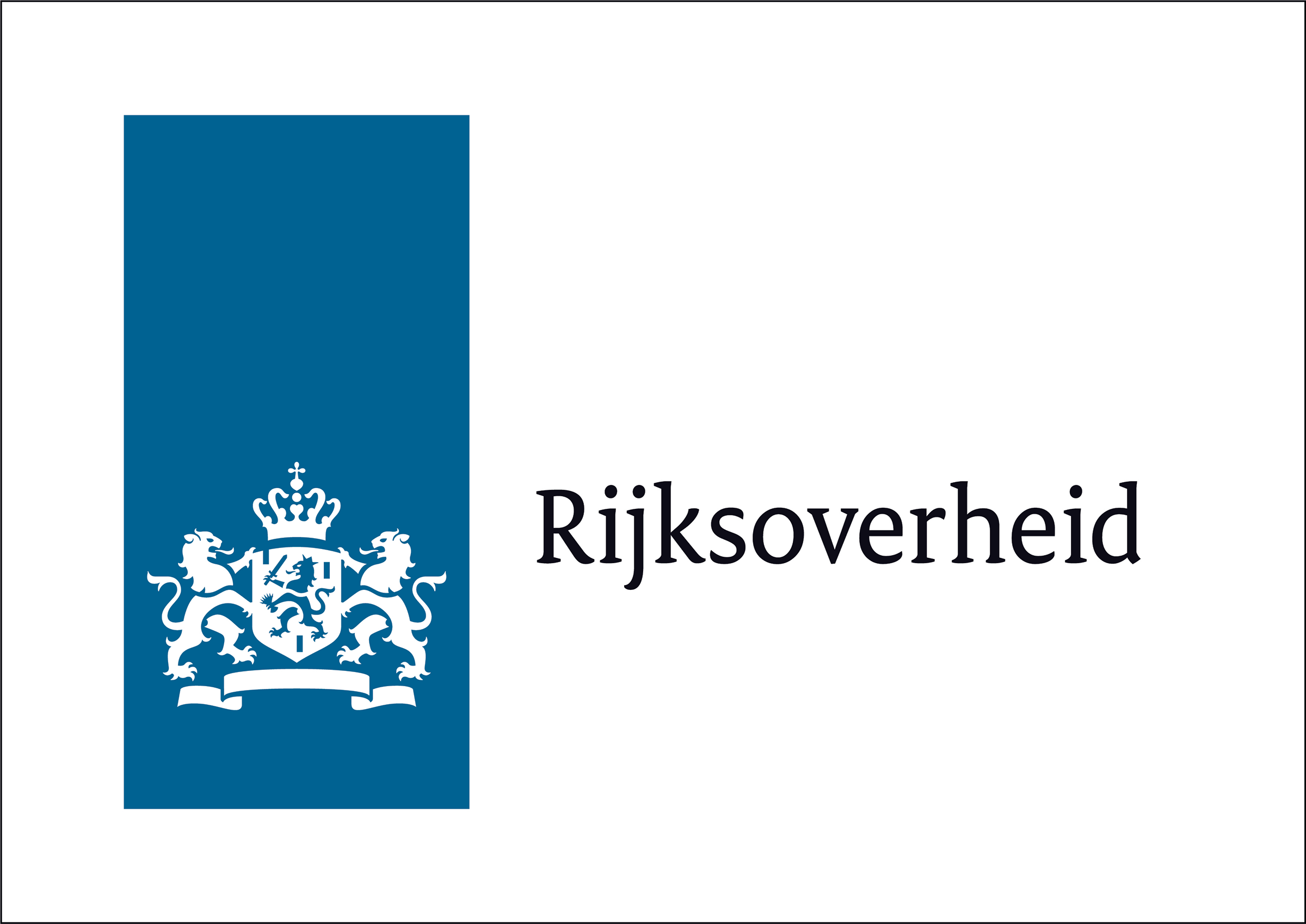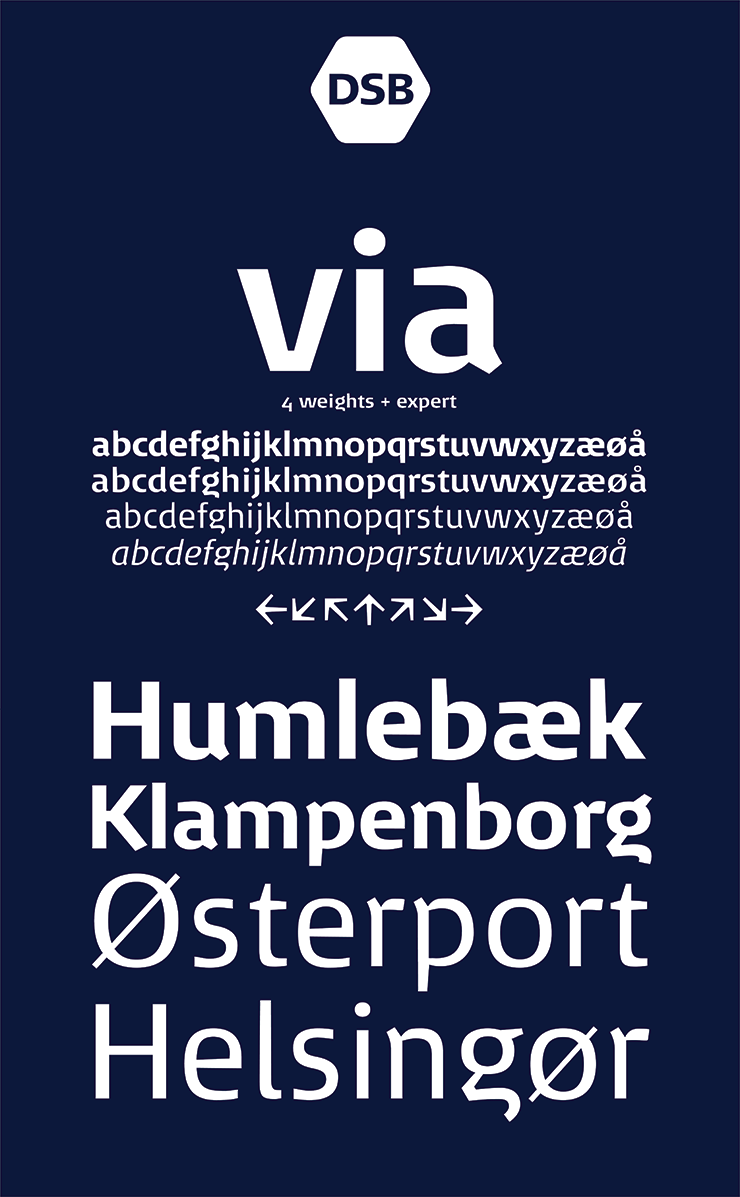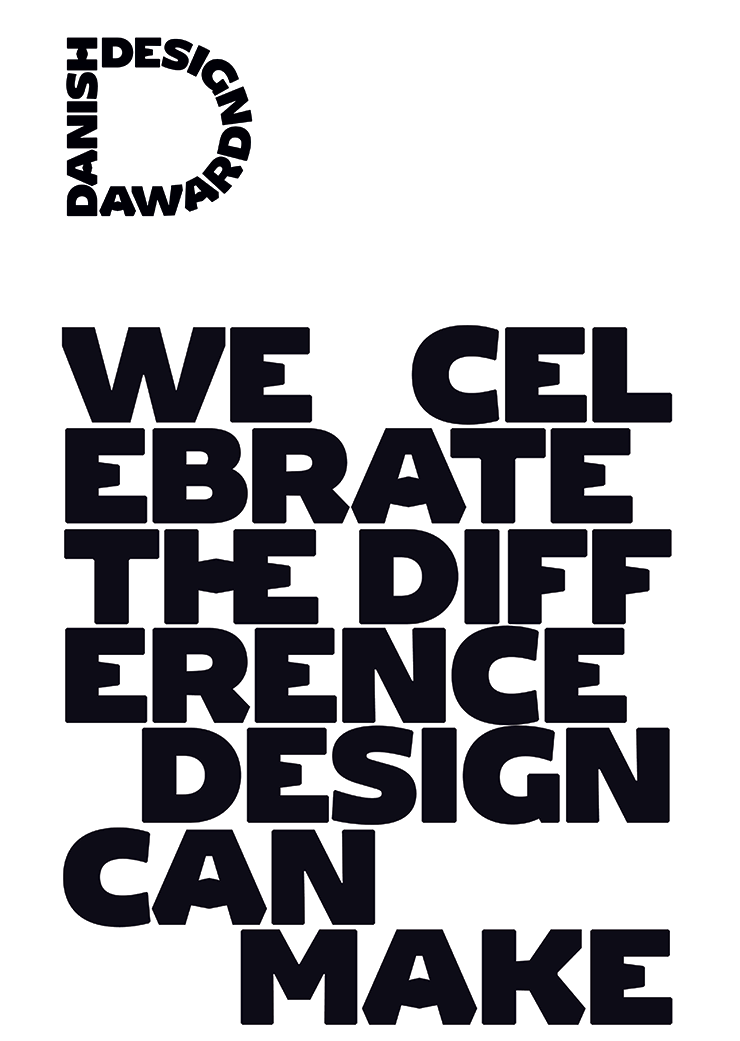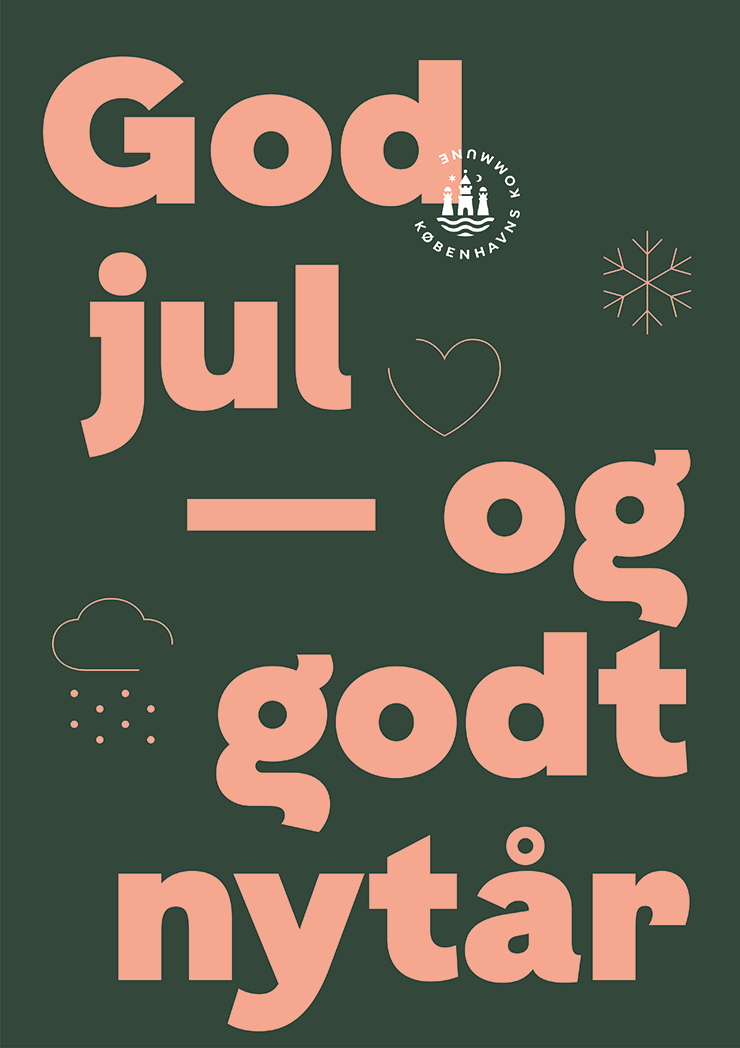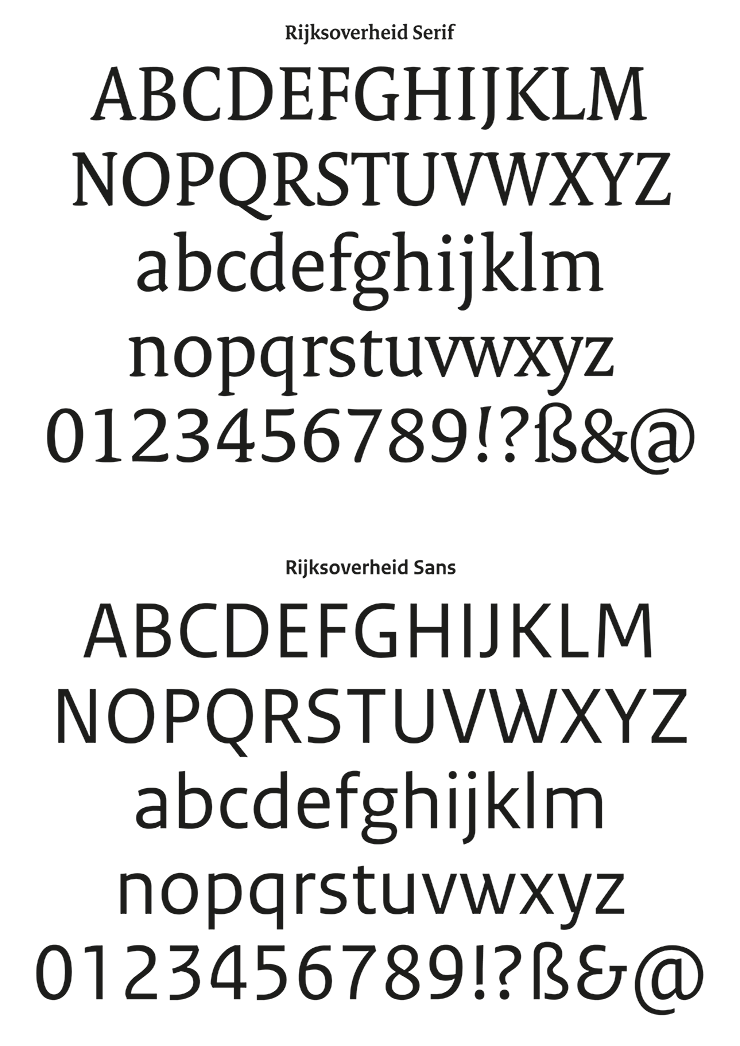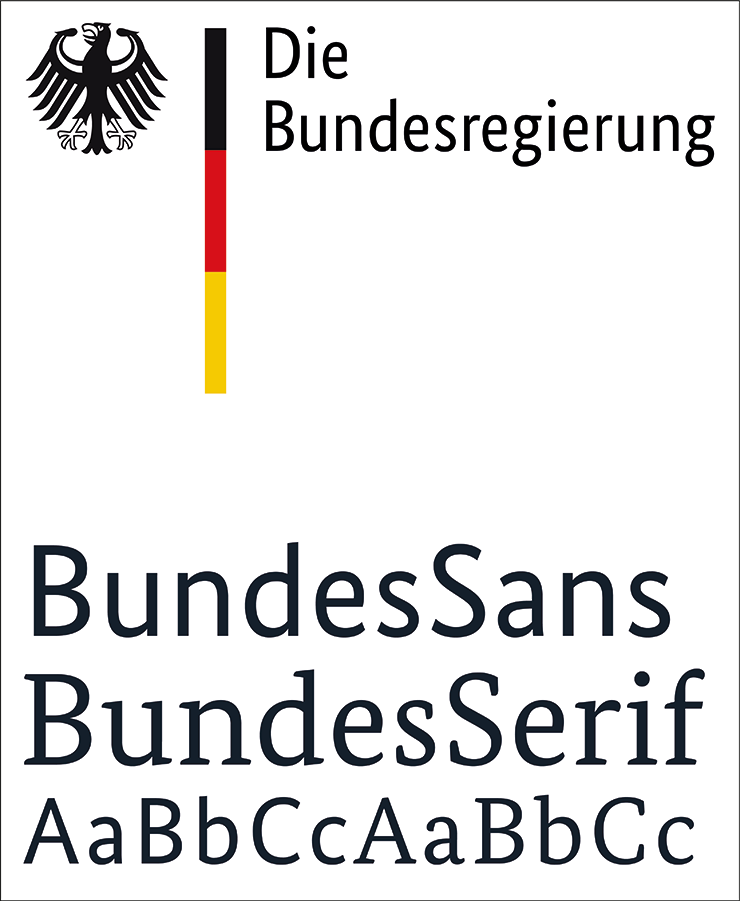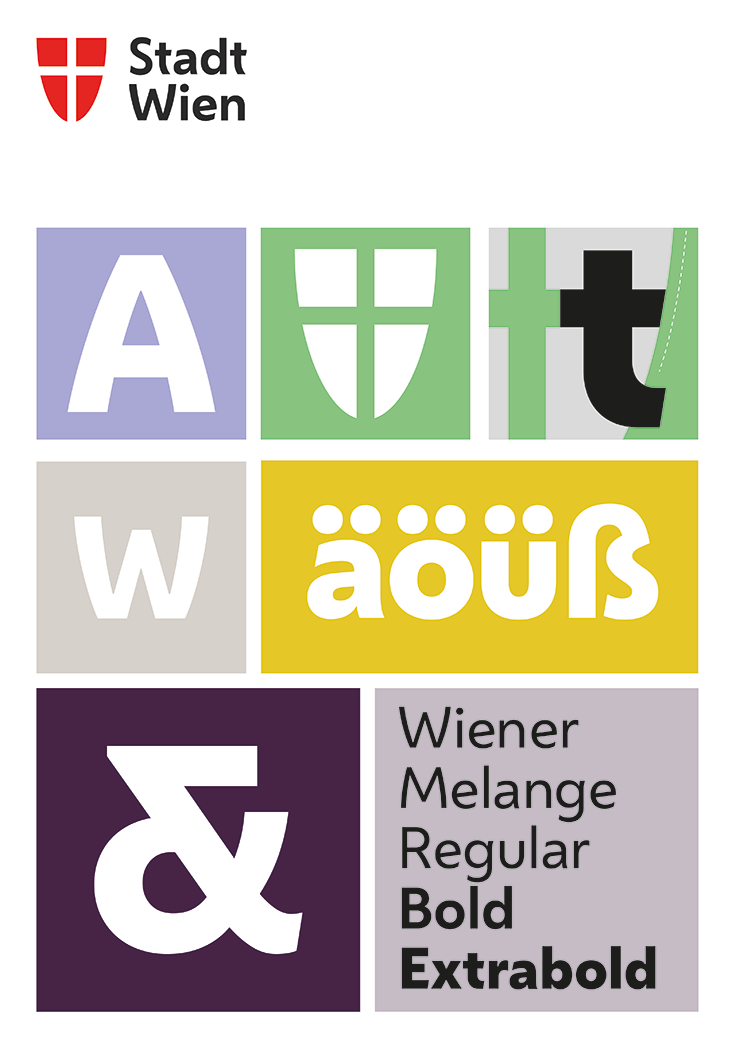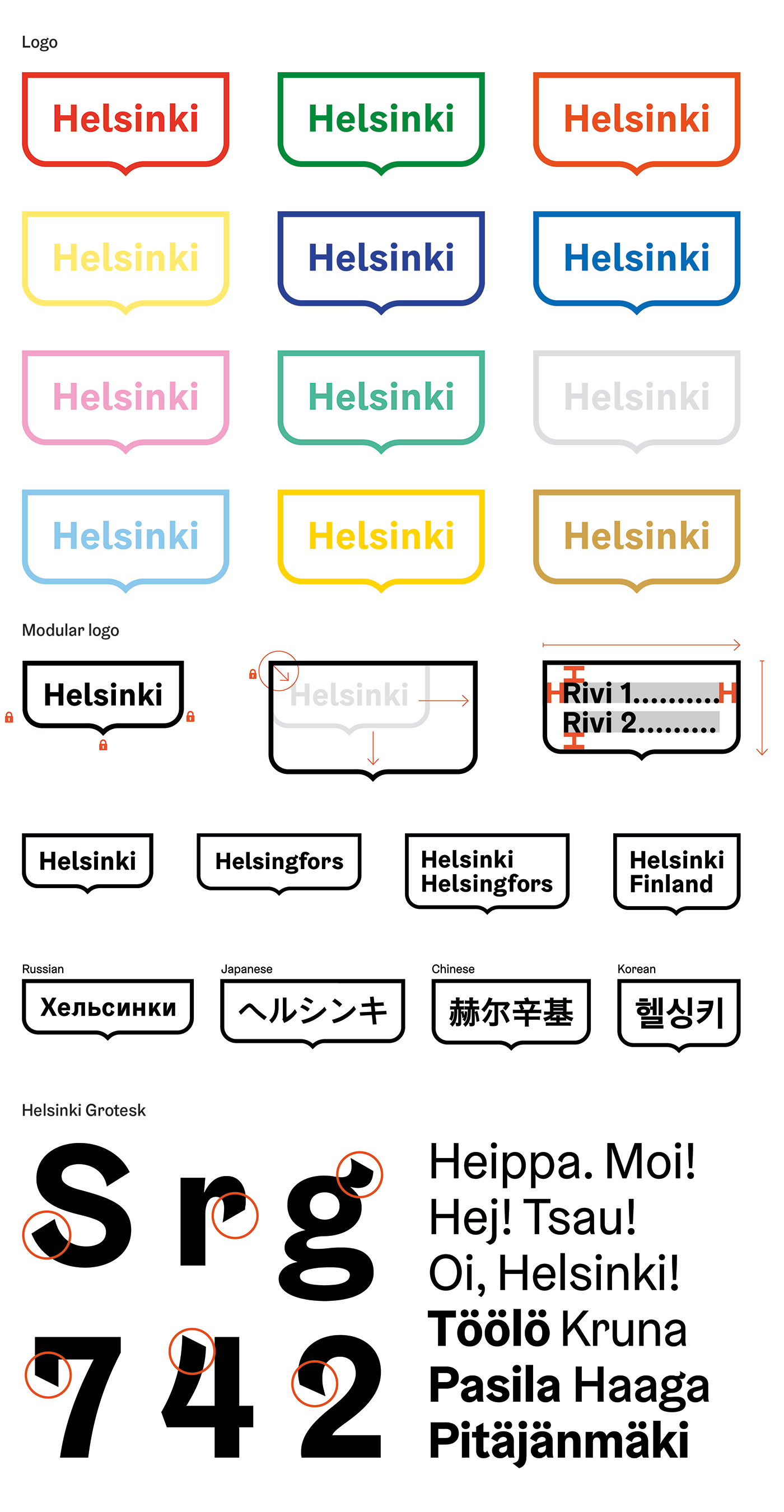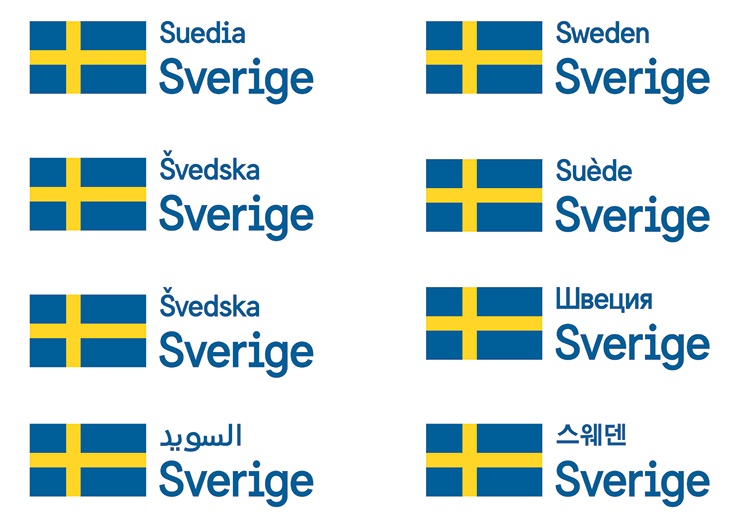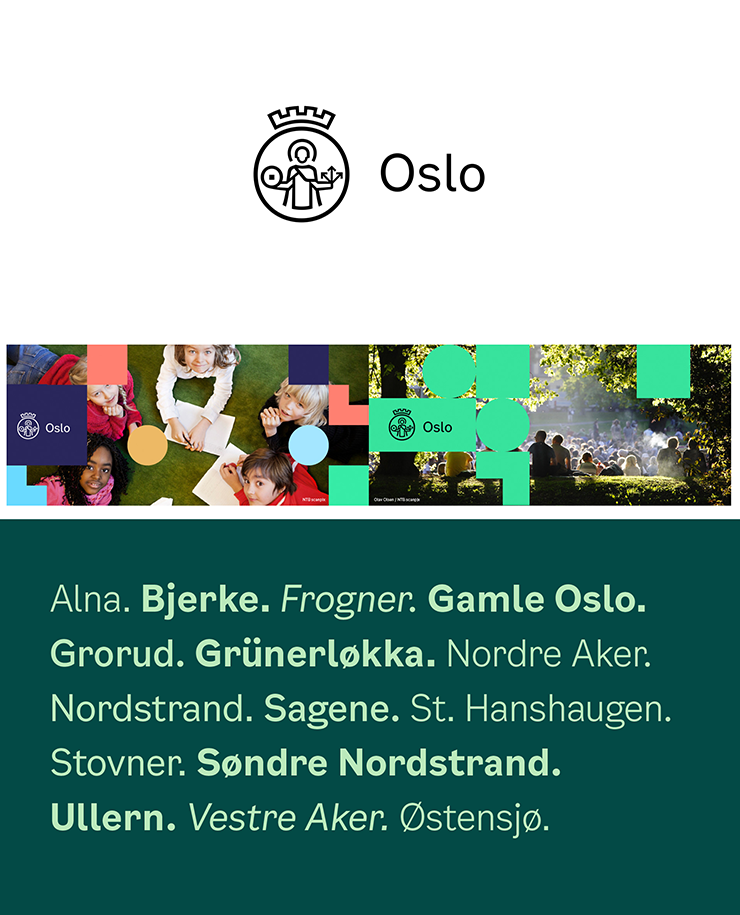
Tipografía, territorio e identidade. A identidade pública a través da tipografía personalizada
A identidade corporativa transita nas últimas décadas dende a preferencia polo símbolo ao desenvolvemento de programas flexibles e escalables no que a tipografía colocouse nun lugar de privilexio desenvolvendo un novo rol. Aqueles elementos identificadores básicos –nome, imagotipo, logotipo– deixaron de ser en solitario ferramentas para o éxito nun mundo cun crecente número de soportes, tecnoloxías e contextos aos que debe atender una marca. Neste horizonte a creación de tipografías «personalizadas» ocupa un novo rol, gañando un lugar destacado dentro deses elementos identificadores. Nas marcas territoriais observamos esta tendencia tipográfica, favorecida polas estratexias identificadoras cos elementos territoriais co obxectivo de proxectarse cara ó exterior dende a diferenza.
A identidade corporativa: da estandarización tipográfica á personalización
A creación de tipografías personalizadas como elemento central de identidades corporativas non é unha práctica novidosa. Xa dende principios do século XX podemos observar exemplos como os da tipografía de Edward Johnston para o metro de Londres en 1916, que configurou unha identidade visual non só dun servizo público, senón dalgunha maneira de toda unha cidade. Sen embargo, o triunfo do Proxecto Moderno, especialmente despois da II Guerra Mundial e ata a chegada da Posmodernidade, trouxo consigo unha demanda de comunicación universal que encamiñou ao deseño cara á estandarización. Baixo esta idea de universalidade xurdiron novos plantexamentos tipográficos difundidos nas escolas de deseño máis influentes de Europa (Zurich, Basilea, Ulm…). Un dos fundadores da Escola de Ulm, o deseñador suízo Max Bill concibía a tipografía como «… deseño modular, como un edificio, unha cuestión de organización de pezas producidas mecanicamente como parte dunha estrutura [1]». Emerxe para este propósito unha nova categoría tipográfica, as neo-grotescas, que intentan transmitir unha mensaxe clara e sen interferencias, independentemente do contexto, un racionalismo que pretendía amosar as expresións visuais dun mundo moderno de xeito obxectivo, claro e efectivo. Estas tipografías usadas de xeito recorrente en proxectos de identidade corporativa foron o exemplo máis claro dunha planificación racional, pero anularon toda personalización e singularidade tipográfica.
A chegada da Posmodernidade a finais dos 70’, supuxo unha ruptura nesa liña de evolución da identidade corporativa. Explorou camiños como o revival e a deconstrucción, e o símbolo recuperou o seu protagonismo cunha formulación máis libre e expresiva. O pensamento matemático e a retícula deron paso ao layout en diferentes capas visuais. A tipografía como solución de problemas de comunicación deu paso á personalización para un uso concreto, aferrado ao lugar e ao contexto. As identidades corporativas xa non so transmitían identidade a través dos elementos básicos senon que a tipografía ofrecía tamén ese rol identificador singular, en ocasións substituíndo o protagonismo do imagotipo.
O cambio de milenio adentrounos nunha nova era no deseño e trouxo consigo un paso máis na democratización do deseño de tipografías. Os avances na accesibilidade no software de deseño, a inclusión do deseño de tipografía nos programas formativos de escolas e universidades e unha necesidade cada vez maior de diferenciación a través da identidade posibilitaron a creación nas últimas décadas de familias tipográficas con infinitas posibilidades de personalización, pero tamén con un alto nivel técnico. A diferenza da época posmoderna, a tipografía corporativa actual está constituída por amplas familias e variantes versátiles en todos e cada uno dos soportes, formatos e contextos dunha marca. Revelouse como un potente instrumento de xeración de identidade, recoñecemento e pregnancia, e nun dos elementos do deseño máis completos e efectivos. As tipografías corporativas deseñadas ad hoc ofrecen hoxe en día unha atención especializada a todos os soportes dunha marca, aos idiomas dos potenciais clientes e ás necesidades cambiantes na comunicación. Esta versatilidade é aproveitada hoxe en día polas identidades do ámbito territorial-político. Os gobernos, rexións e cidades son entidades que posúen hoxe todo tipo de necesidades de comunicación, dende os soportes tradicionais aos dixitais, e dende a atención aos seus habitantes en cuestións burocráticas ás cuestións de promoción turística no ámbito global. Neste escenario, poder personalizar a tipografía corporativa para abarcar todos estes ámbitos é unha estratexia en alza.
As marcas territoriais
A construción de marcas territoriais no transcurso das últimas dúas décadas supuxo unha importante vía de investigación no ámbitos do deseño e o branding. Dende o ámbito local ao alcance global, ás tradicionais diferenciacións do territorio dende o punto de vista administrativo e político, sumáronselle cuestións de promoción turística, cultural e oportunidades de negocio. Tal e como afirma ao respecto o experto en creación de marcas Wally Olins:
«Agora todas as nacións tratan de promover a súa personalidade, a súa cultura, a súa historia e os seus valores individuais co fin de proxectar unha imaxe idealizada, pero inmediatamente identificable, de si con fines económicos e comerciais ademais de políticos. Estas pretensións levan aos países a adoptar técnicas de branding e marketing que con tanto éxito e dende fai tanto tempo utilizan moitas empresas globais [2]».
Xeráronse unhas necesidades de diferenciación identitaria non exentas do paradoxo de pretender unha proxección global a partir dunha identidade local. Isto favoreceu as estratexias propias do ámbito empresarial e cada vez máis termos como o de «marca-país» están sendo asimilados como estratexias globais. Ás cuestións de poder político, influencia no mundo e prestixio, sumáronselle aspectos materiais e cuantificables, como as inversións extranxeiras, as exportacións de produtos e o turismo. Os arraigos ao lugar, especialmente naqueles sitios onde existe unha intención identificadora cos elementos nacionais dunha rica tradición, nutren o terreo do deseño de marcas, e a tipografía personalizada enraizada na súa tradición encaixa á perfección como un elemento máis dentro desa estratexia da diferenciación con respecto aos seus competidores, salientando a cultura, a tradición, a historia, a paisaxe, o patrimonio gastronómico e o arquitectónico.
Figura 1: Logotipo do goberno dos Países Baixos do Studio Dumbar coa tipografía personalizada Rijksoverheid Serif (2008).
En moitas ocasións a tipografía úsase como un elemento unificador cuxa misión é a de integración e vertebración de todas as variantes dunha marca. Nestes casos transcende ao logotipo, sistematiza e reunifica diferentes marcas e submarcas dunha mesma identidade. Ocorre con frecuencia no caso das marcas de gobernos e institucións cunha grande cantidade de identificadores. O proxecto de Studio Dumbar para a identidade do goberno dos Países Baixos [3] [Figura 1] en 2008, integrou na súa arquitectura de marca as 175 identidades gobernamentais dispersas que existían ata ese momento. Como elemento unificador creouse unha tipografía personalizada [Figura 2] deseñada por Peter Verheul [4], recollendo ademais a rica tradición tipográfica holandesa. Este proxecto do goberno dos Países Baixos é un exemplo claro do poder do deseño e a tipografía para a creación dunha imaxe unificada e da influencia directa do deseño na percepción do labor político dun goberno por parte dos cidadáns. O proxecto plantexase a partir dunha crisis política de identidade do goberno da CDU de Jan Peter Balkenende en 2006. Ante a necesidade de optimizar os recursos decidiuse impulsar a colaboración entre os diferentes ministerios e áreas. O reflexo desta colaboración foi a creación dun único logotipo baseado na figura do león característico do escudo holandés tradicional, xunto con unha tipografía que identificase os diferentes ministerios e áreas. O deseño da tipografía de Verheul partiu doutro tipo, a Versa do seu mesmo autor, dándolle un carácter máis distintivo, con remates cónicos e asimétricos, engadindo ademais unha versión lineal humanística máis neutra para ampliar o rango de soportes e a súa versatilidade.
Figura 2: Tipografía Rijksoverheid Serif e Sans deseñada por Peter Verheul para o proxecto de identidade corporativa do Studio Dumbar.
Un caso similar o atopamos no goberno alemán [Figura 3]. Dende que en 1996 Lisa Eidt e Jürgen Huber deseñaran a identidade visual do goberno, a súa tipografía corporativa foi variando dende a Univers inicialmente proposta á FF Transit de 1997 usada por Metadesign. Finalmente en 2017 a axencia Adlerschmidt propuxo a creación da tipografía Bundes ao estudio Supertype co obxectivo de unificar unha soa voz tipográfica á vez que atendía ao desafío dunhas necesidades de comunicación dun grupo de poboación moi amplo, mellorando a lexibilidade en soportes dixitais e tradicionais.
Figura 3: Logotipo do goberno alemán coa tipografía personalizada Bundes Sans e Bundes Serif deseñada pola fundición Supertype (2017).
[12] O denominado hinting é o uso de instrucións matemáticas co obxectivo de optimizar a visualización dunha fonte vectorial en soporte pantalla. Esencialmente consiste en axustar as súas formas á retícula de píxeles indicándolle ao software encargado da súa rasterización como debe mostrar as súas formas, especialmente en tamaños pequenos. A chegada das pantallas de alta resolución en dispositivos móbiles e tabletas fixeron que cada vez sexa menos necesario a atención ao hinting e todo indica que nun futuro próximo non será un asunto crítico.